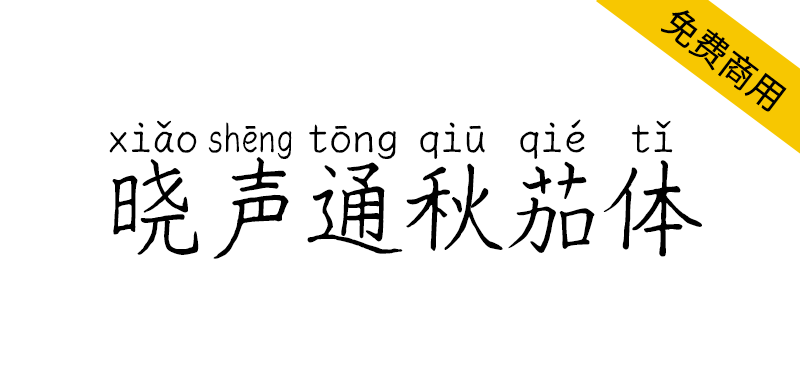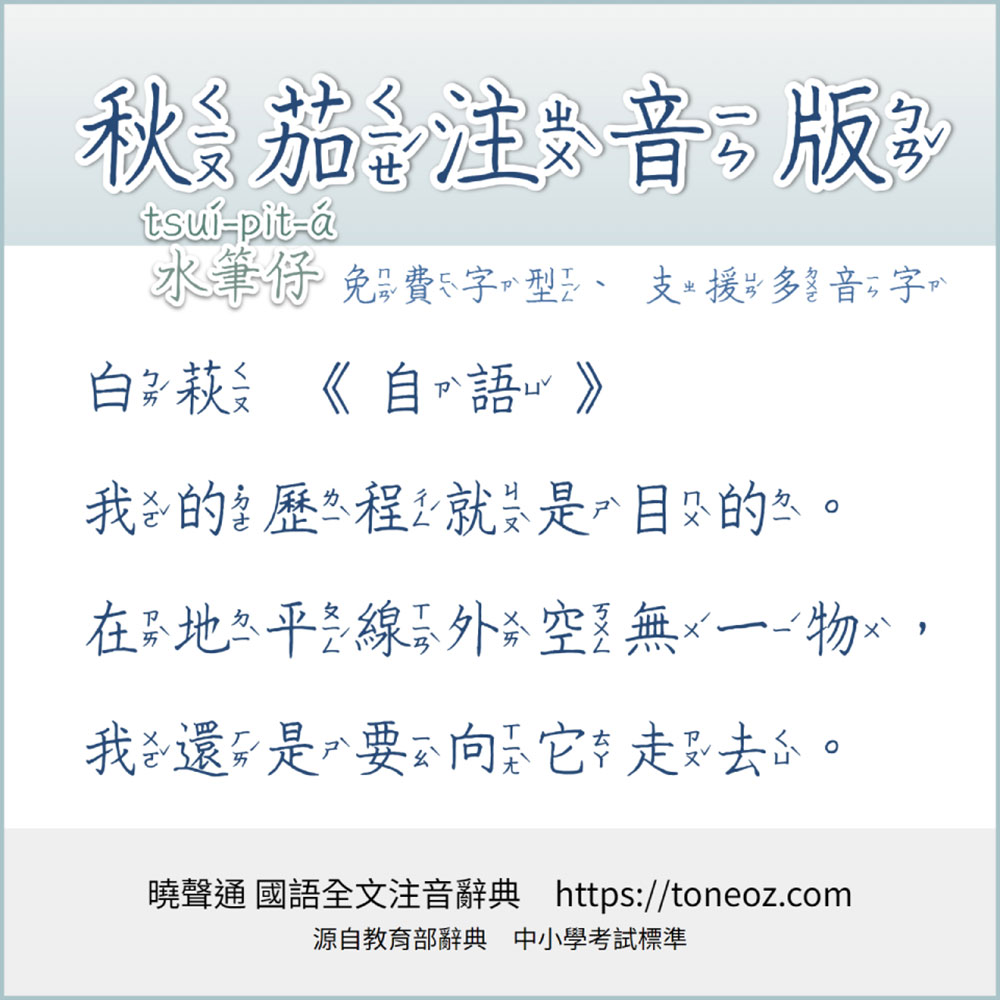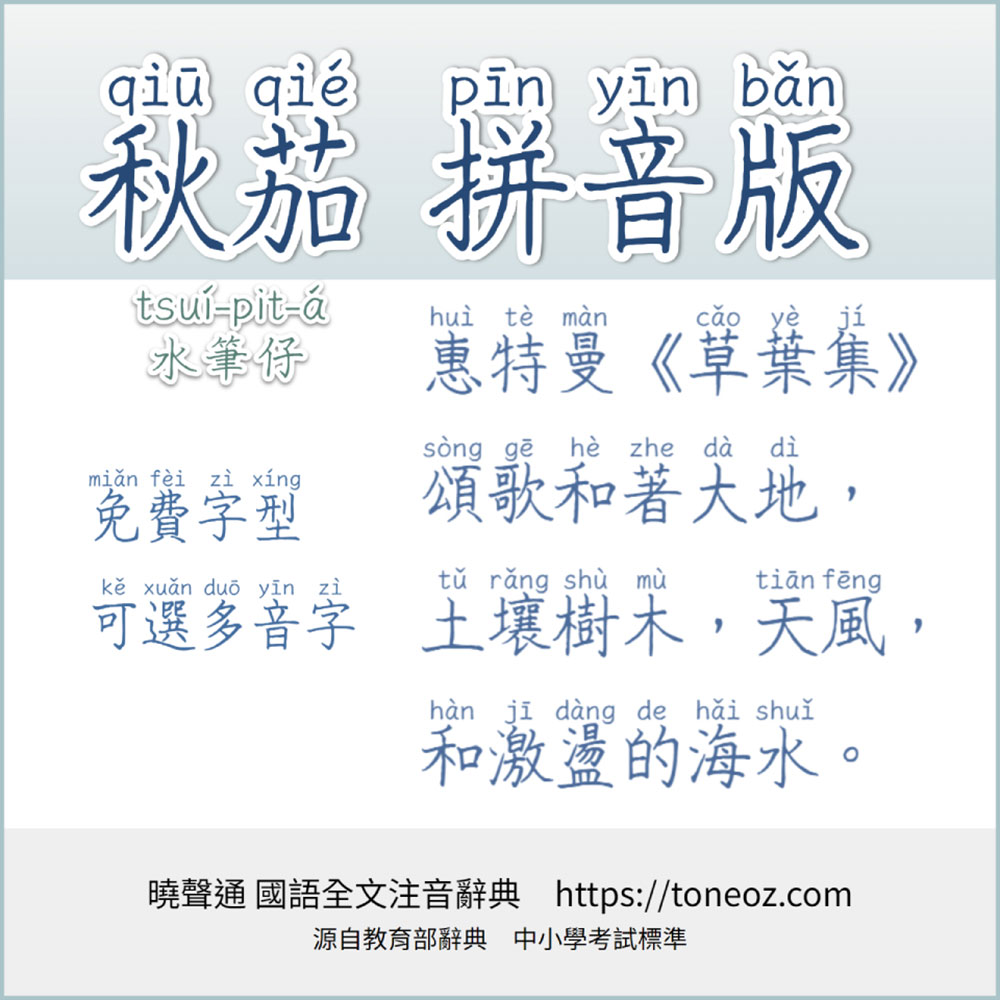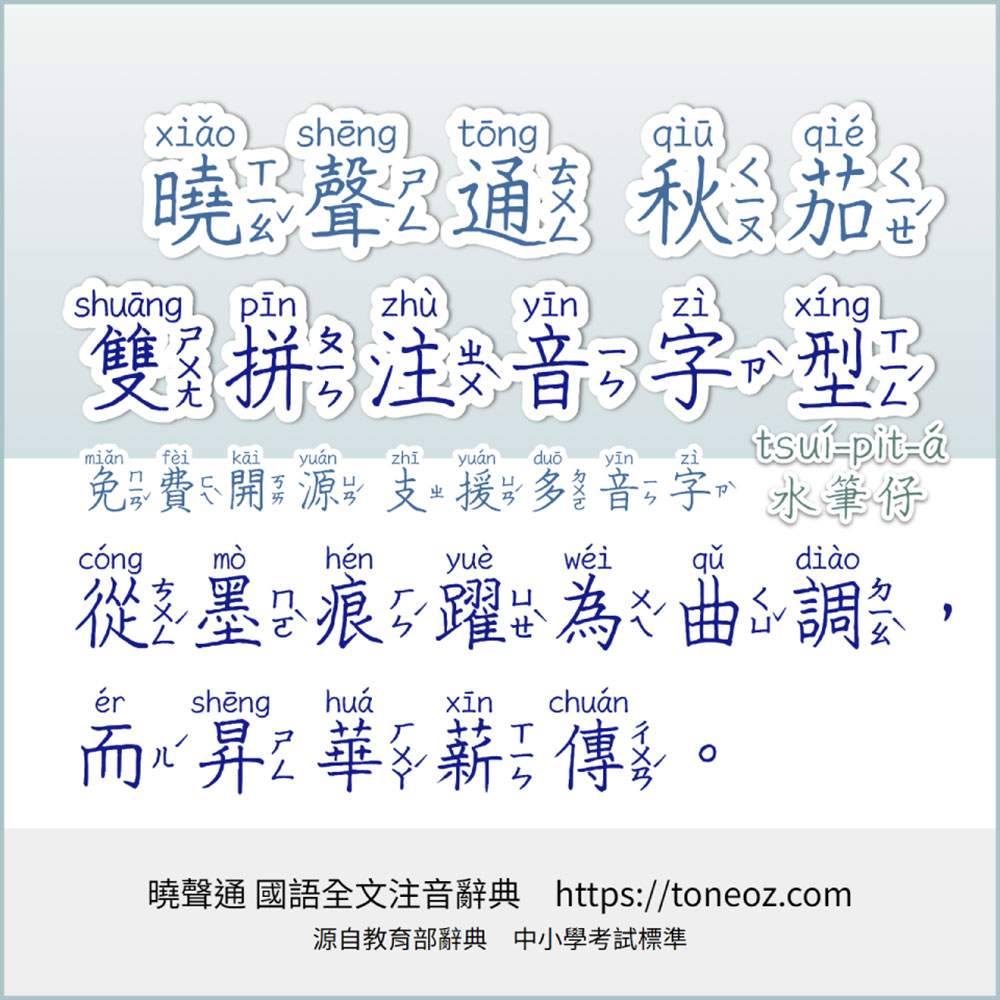
晓声通「秋茄体」是开源免费的手写字型,中性签字笔风格,笔形符合国语教学《教师手册》,由教育全文注音国语辞典「晓声通」开发,涵盖「教育部国语辞典」全条目,中小学考试标准「简编本」常用字、及「重编本」「成语本」生僻字。以国字标准为前提,支援多元文化教案:闽南语、客家话、日本语、各式拼音、及港澳用字。
「手写字型」常用于诗词、歌曲、人物独白或对话⋯用以提示读者此段文句建议「以人文角度来思考体会」。
市面上有许多优美的手写字型:有些草书字型笔迹奔放、有些美术字型笔触可爱、部分书写时会参杂不同教育标准或通俗写法、有些实作四千~九千常用字而有缺字遗憾…以上多少在教学时带来困扰。
为了辅助教材制作,「晓声通国语注音字典」开发了「秋茄体(水笔仔)」,来帮助老师们轻松创作教案。
晓声通秋茄体除了标准纯汉字版本,另外还有「国语注音」「汉语拼音」及「双拼注音拼音」多音字型版。